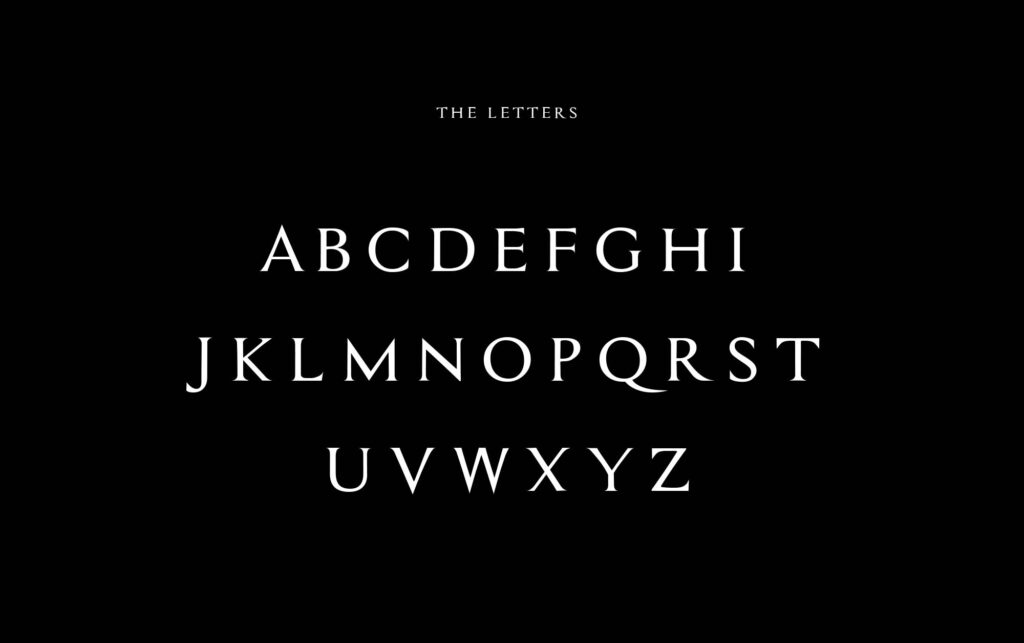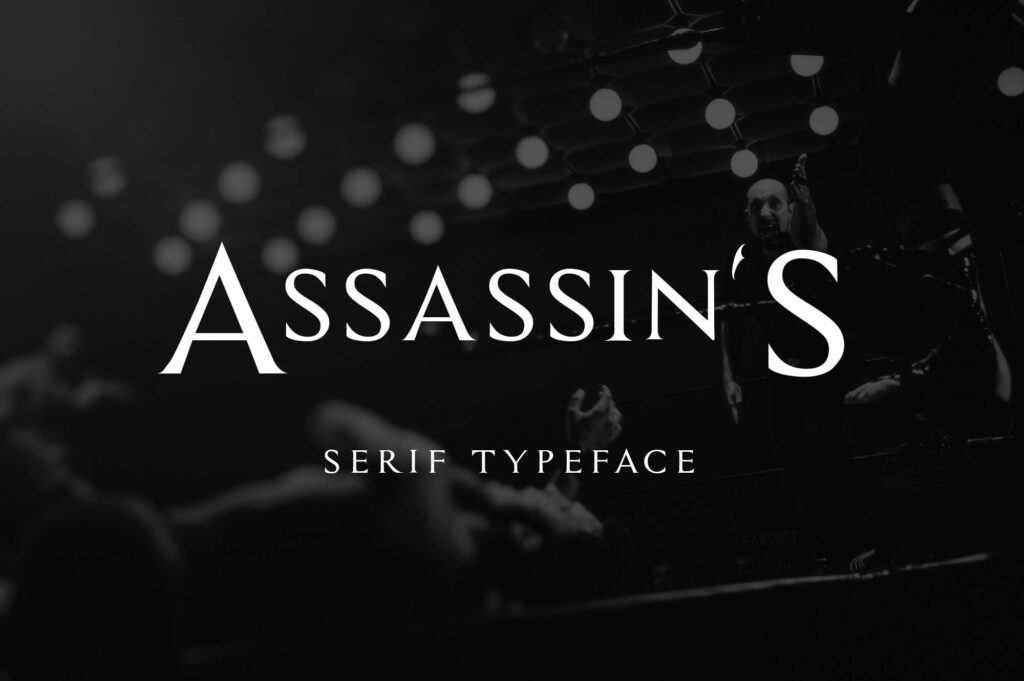
Font UVF Assassin là bộ phông chữ thuộc dòng Display mang phong cách hành động và viễn tưởng, nổi bật với các đường nét vát nhọn sắc sảo mô phỏng hình tượng lưỡi kiếm. Với diện mạo gai góc và đầy tính cơ học, kiểu chữ này thường được các kiến trúc sư, nhà thiết kế lựa chọn để tạo sự bứt phá cho các dự án phòng game, quán cafe phong cách Cyberpunk hay văn phòng công nghệ sáng tạo.
Đặc điểm nhận diện sắc nét của font UVF Assassin trong đồ họa
Nét ấn tượng của font UVF Assassin nằm ở cấu trúc hình học bất đối xứng với các góc cắt dứt khoát, tạo cảm giác chuyển động nhanh và uy lực thị giác lớn. Khác với các dòng phông chữ tiêu chuẩn, mỗi ký tự của bộ phông này đều sở hữu những đường vát mang tính biểu tượng, gợi liên tưởng đến công nghệ tương lai và tinh thần chiến binh. Bản Việt hóa đã xử lý bảng mã Unicode chuẩn xác, giúp các dấu thanh tiếng Việt phối hợp hài hòa cùng các góc cạnh sắc bén mà không làm biến dạng tỷ lệ chữ gốc.
Sự ổn định của bộ chữ còn thể hiện ở khả năng chiếm lĩnh không gian hiển thị. Dù xuất hiện trên bản vẽ 3D hay in ấn thực tế trên các bề mặt vật liệu công nghiệp như thép tấm, alu hay kính, phông chữ vẫn duy trì được độ sắc nét và tính độc bản. Đây là giải pháp phù hợp để định hình cá tính cho các công trình nhà lắp ghép thế hệ mới, văn phòng container phá cách hoặc những thương hiệu muốn khẳng định sự táo bạo và tinh thần tiên phong.
| Phân loại phong cách | Display / Futuristic / Sharp / Action |
| Mục đích phù hợp | Tiêu đề phối cảnh, logo gaming, biển hiệu công nghệ |
Tư vấn từ chuyên viên: UVF Assassin sở hữu cá tính hình khối rất mạnh. Để bản thiết kế đạt hiệu quả thị giác tốt, bạn chỉ nên sử dụng phông chữ này cho các tiêu đề chính hoặc logo. Phần nội dung mô tả kỹ thuật chi tiết nên đi cùng một phông không chân đơn giản để người xem nắm bắt thông tin dễ dàng.
03 Ứng dụng phông chữ UVF Assassin vào thực tế công trình
Nhờ vẻ ngoài giàu tính kích thích thị giác và phong cách cơ học, bộ phông chữ này mang lại giá trị thực tế cao trong khâu tạo điểm nhấn cho các công trình hiện đại:
- Biển hiệu cho phòng Game và Studio công nghệ: Những nét cắt vát sắc sảo của font UVF Assassin rất ăn ý khi kết hợp cùng đèn LED neon trên nền tôn sóng của nhà container, mang lại một không gian đậm chất viễn tưởng và thu hút giới trẻ.
- Hệ thống nhận diện cho câu lạc bộ thể thao: Sử dụng phông chữ này để làm biển tên hoặc trang trí tường tại các phòng tập thể hình, câu lạc bộ võ thuật lắp ghép giúp khơi gợi tinh thần rèn luyện và năng lượng bùng nổ.
- Trang trí không gian nội thất phong cách Industrial: Bạn có thể dùng phông chữ này để cắt CNC trên vật liệu kim loại hoặc mica đen mờ làm tranh trích dẫn, tạo nên điểm nhấn cá tính cho sảnh chờ văn phòng.
03 Lưu ý kỹ thuật để bố cục font UVF Assassin hài hòa và không rối mắt
Để khai thác hiệu quả vẻ đẹp của dòng font hành động này mà không gây cảm giác khó chịu cho người đọc, người thiết kế nên lưu tâm một số kinh nghiệm sau:
- Hạn chế dùng cho đoạn văn dài: Cấu trúc vát cạnh của phông chữ có thể gây mỏi mắt nếu trình bày ở kích thước nhỏ với mật độ dày đặc. Hãy dành riêng nó cho các từ khóa ngắn, số hiệu phòng hoặc tên công trình.
- Giữ khoảng thở cho chữ: Do các ký tự có nhiều nét nhọn vươn ra ngoài, bạn nên bố trí khoảng trống xung quanh tiêu đề rộng rãi để các nét cắt sắc sảo được hiển thị trọn vẹn, không bị đè lên các chi tiết đồ họa khác.
- Lựa chọn màu sắc tương phản cao: Phông chữ phát huy hiệu quả thị giác tốt khi kết hợp cùng các gam màu lạnh như xám kim loại, đỏ tươi, xanh dạ quang hoặc trắng trên nền đen, làm nổi bật cấu trúc hình học đặc thù của chữ.